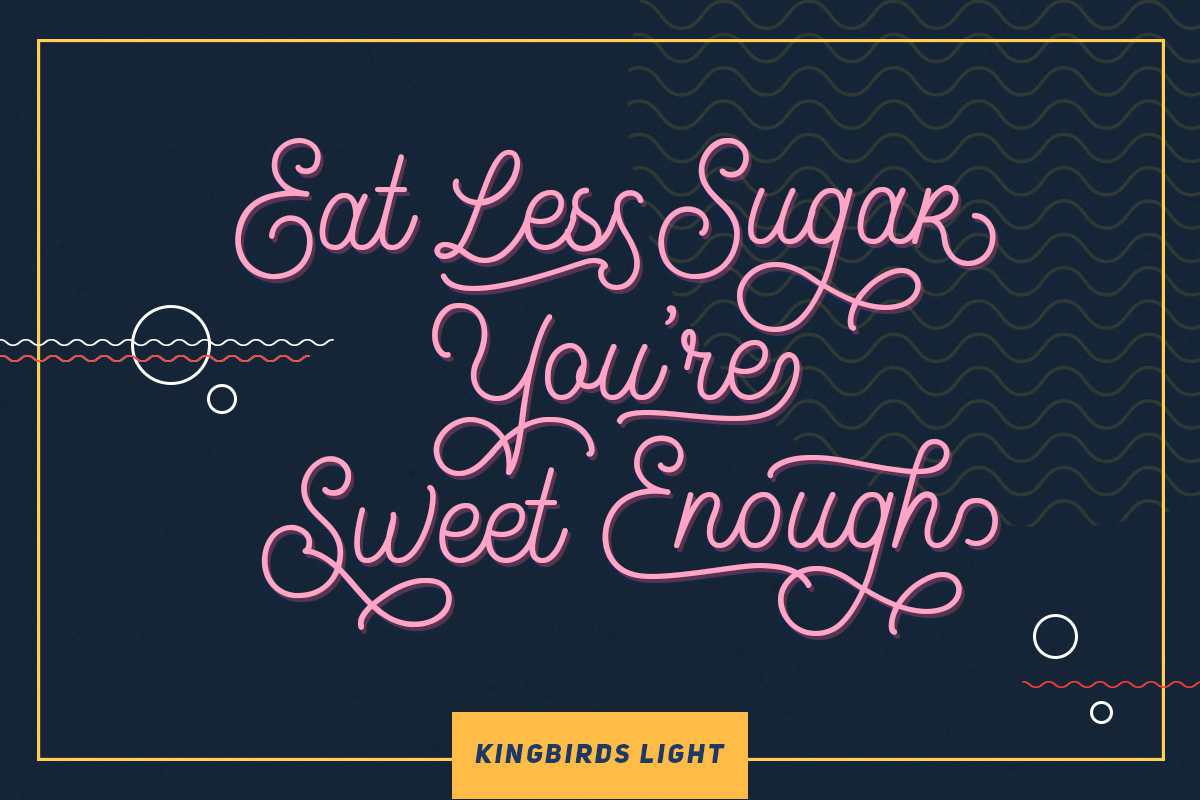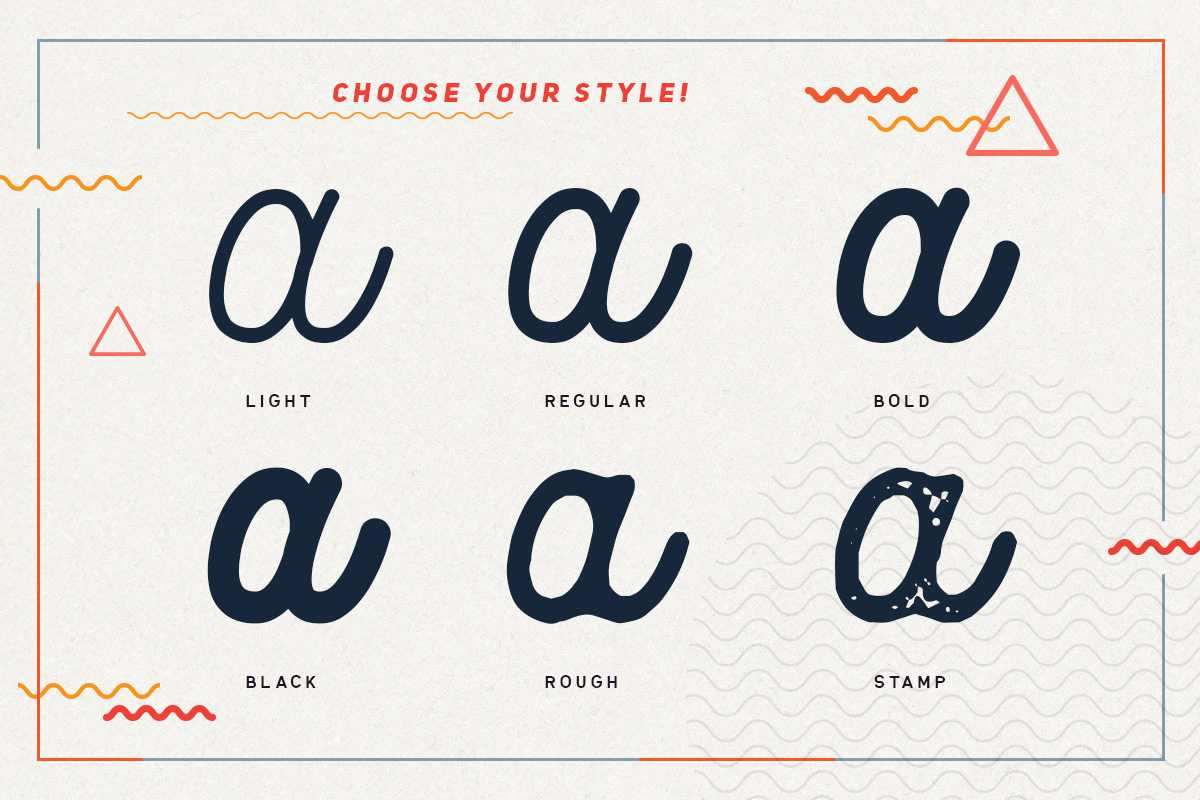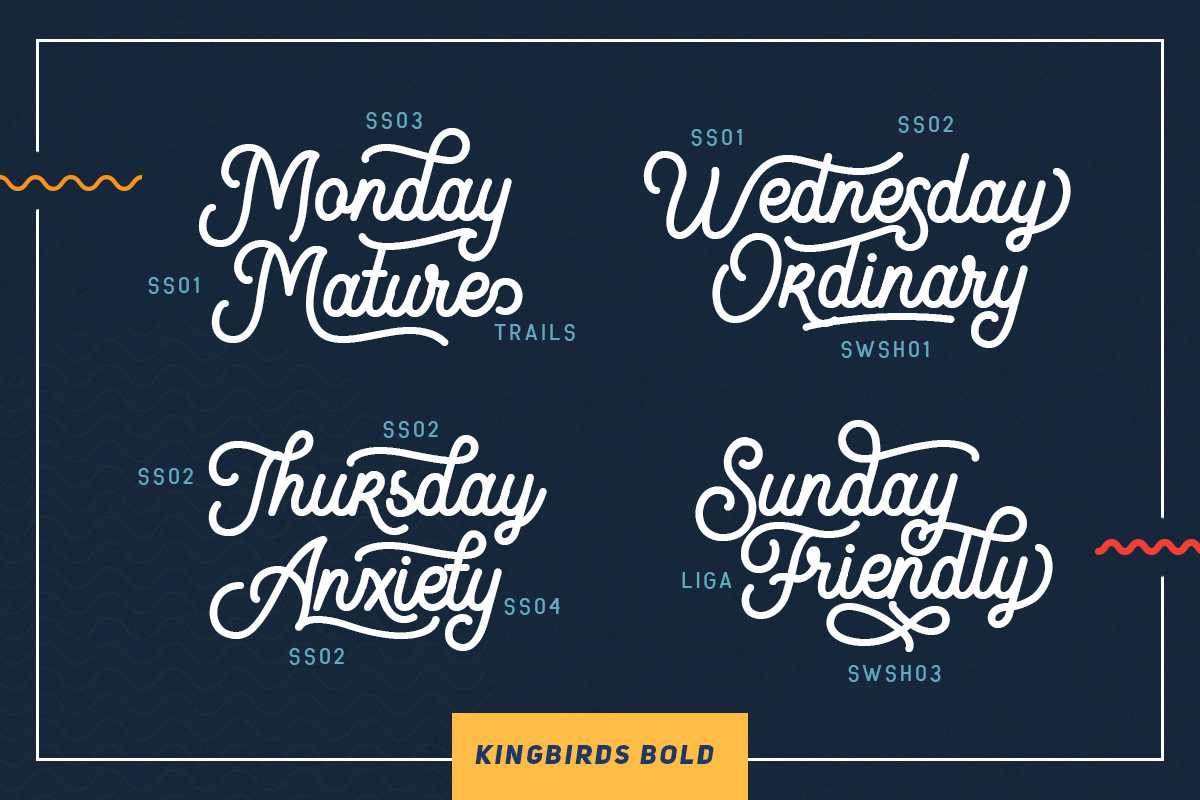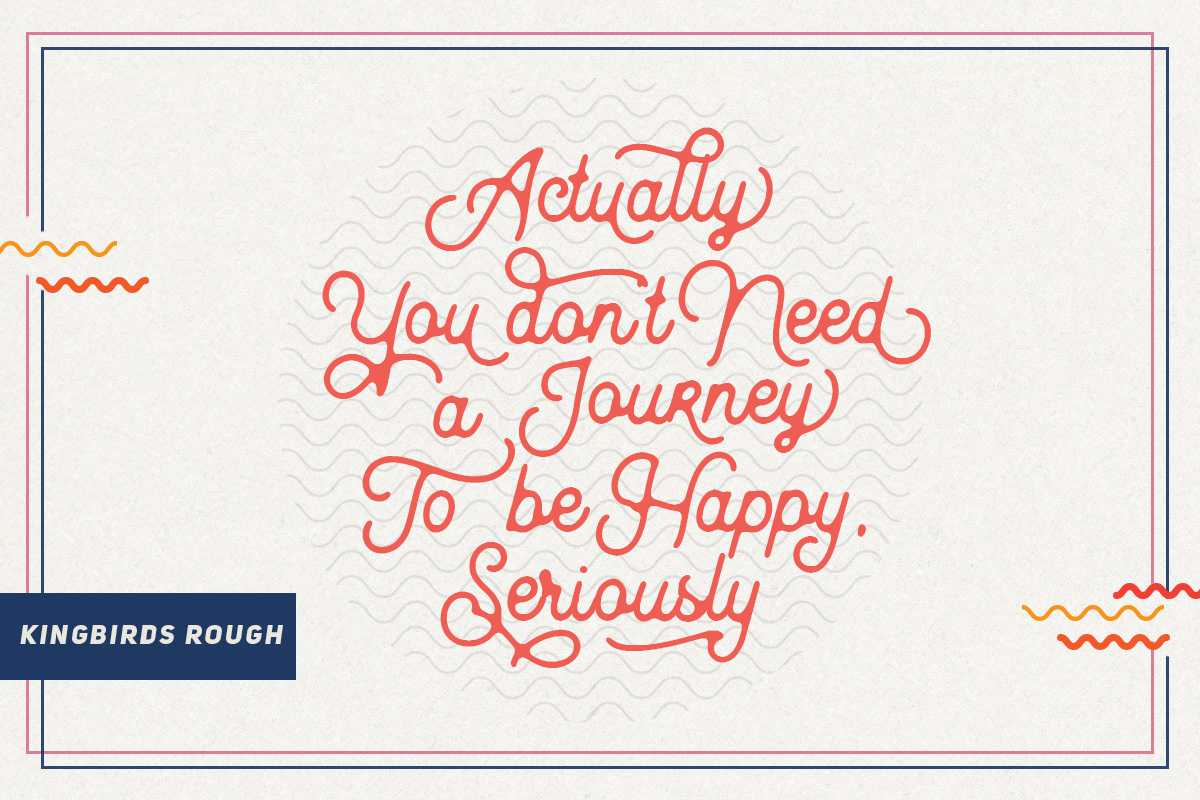
王鸟!6种风格的单线脚本!厌倦了纯在线剧本?现在,我们正在为您呈现一种独一无二的独白剧本,这种独白剧本具有多种风格,可以完全满足设计需求。好玩的主题?优雅的主题?年份名称?您可以命名。这种字体具有任何开放式特征,包括连字、风格设置和替换,ETC还支持多语言。您还将准备好使用Logo模板,以便轻松编辑文本。Kingbirds!6种风格的单线脚本!厌倦了纯在线剧本?现在,我们正在为您呈现一种独一无二的独白剧本,这种独白剧本具有多种风格,可以完全满足设计需求。好玩的主题?优雅的主题?年份名称?您可以命名。这种字体具有任何开放式特征,包括连字、风格设置和替换,ETC还支持多语言。您还将准备好使用Logo模板,以便轻松编辑文本。